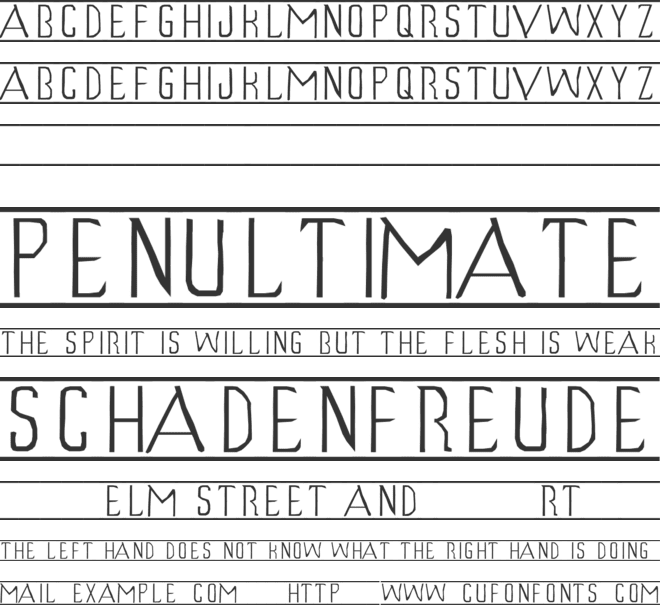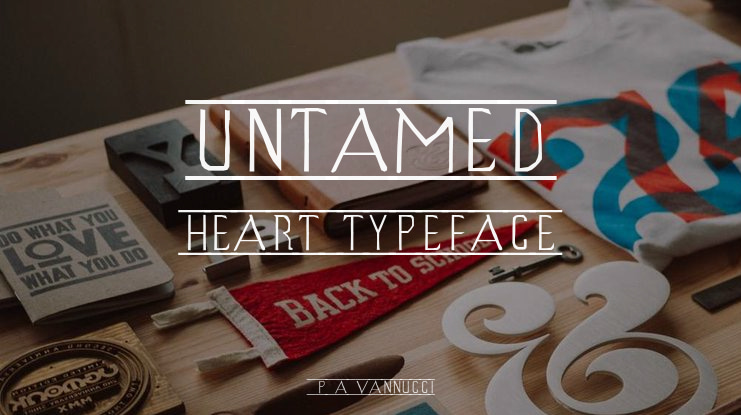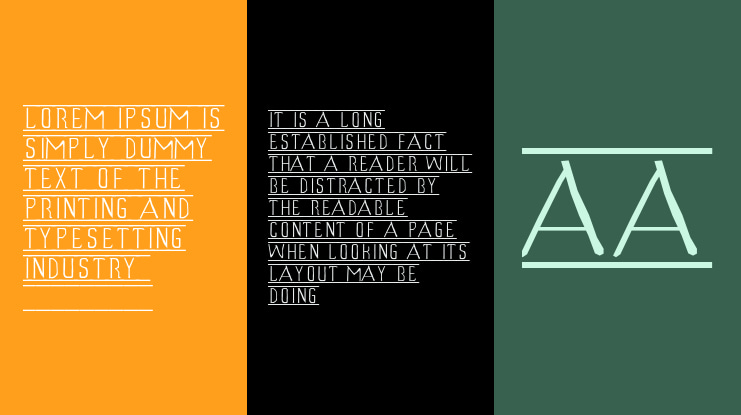
UNTAMED HEART Font
P.A.Vannucci
QUALCUNO DA AMARE font: direttamente dal film diretto da Tony Bill e interpretato da Christian Slater, il font inedito per tutti
gli estimatori del film. Da notare il ritocco necessario in Photoshop per conferire, alla titolazione, l'originale bordatura.
UNTAMED HEART font: directly from the Best movie by Tony Bill, with Christian Slater, the original font for all lovers. Use ADOBE Photoshop for the original border from title.